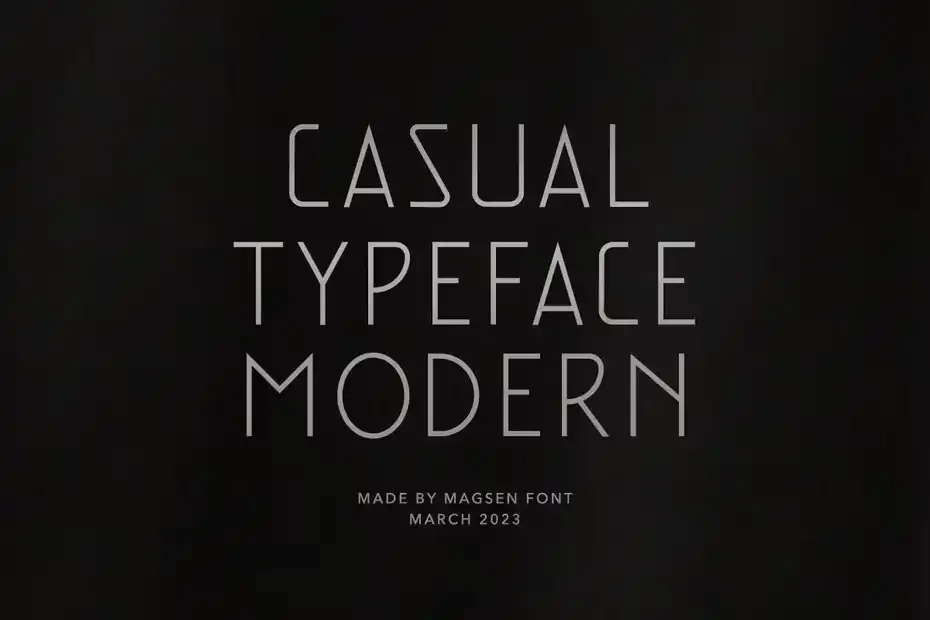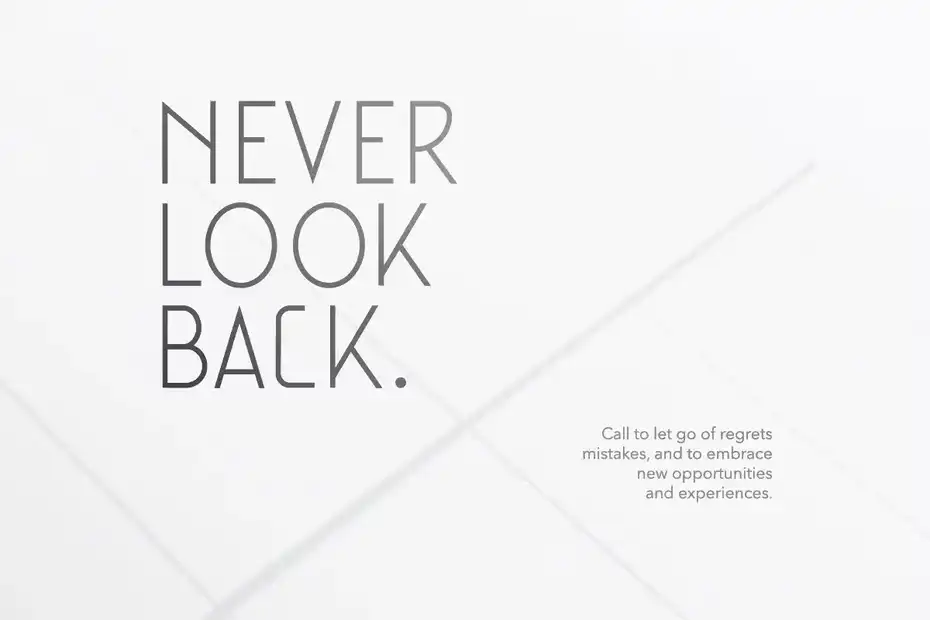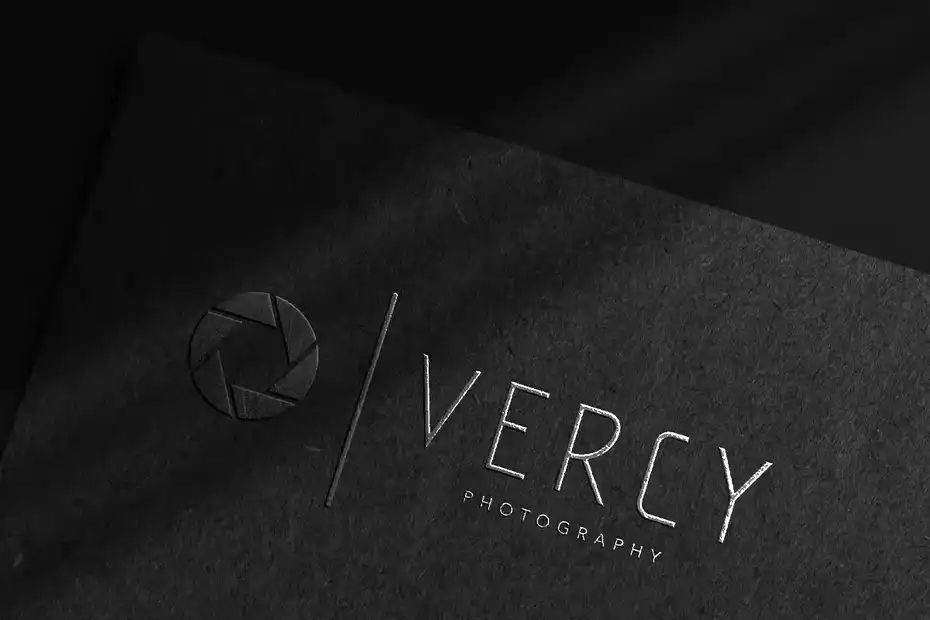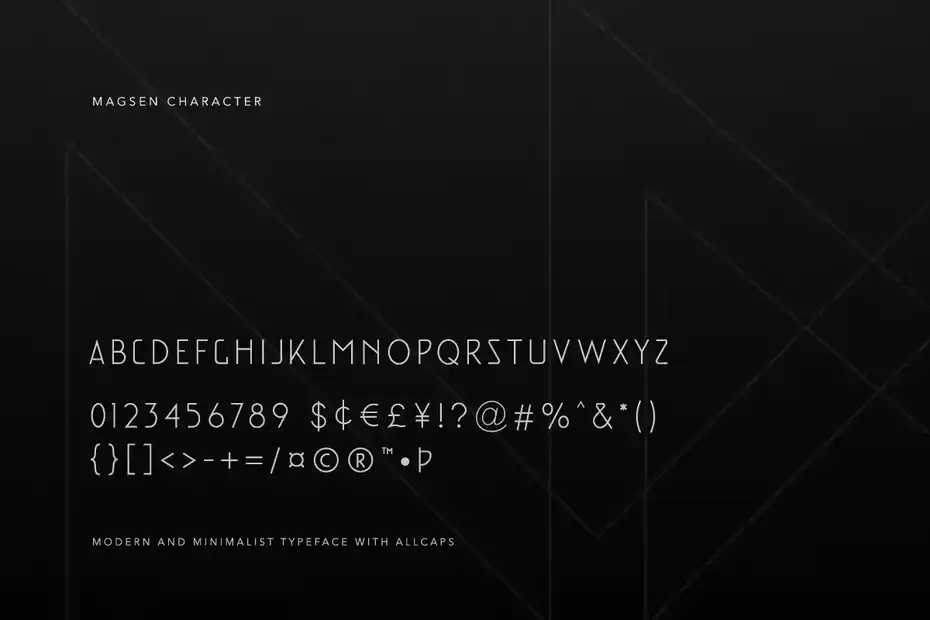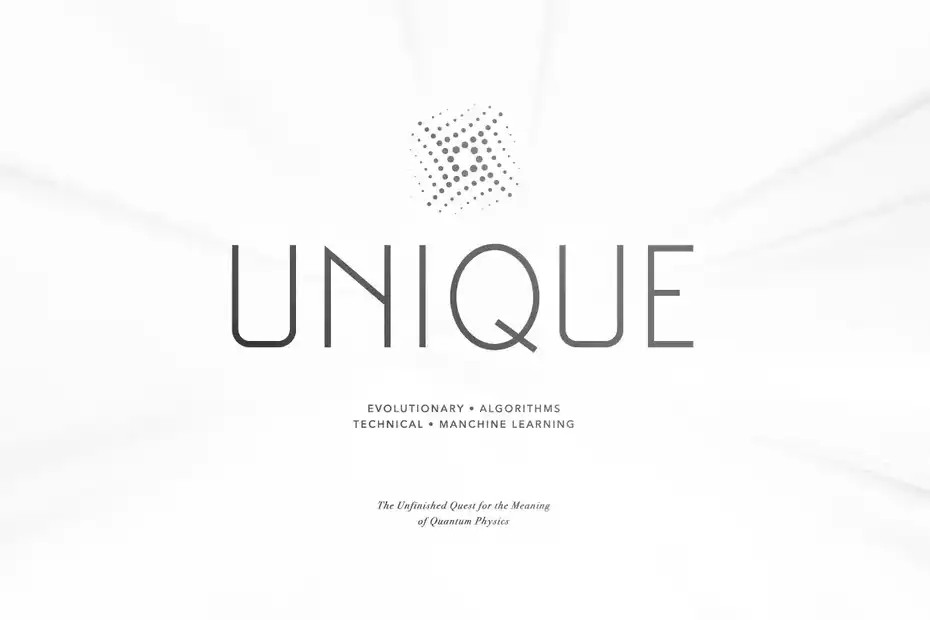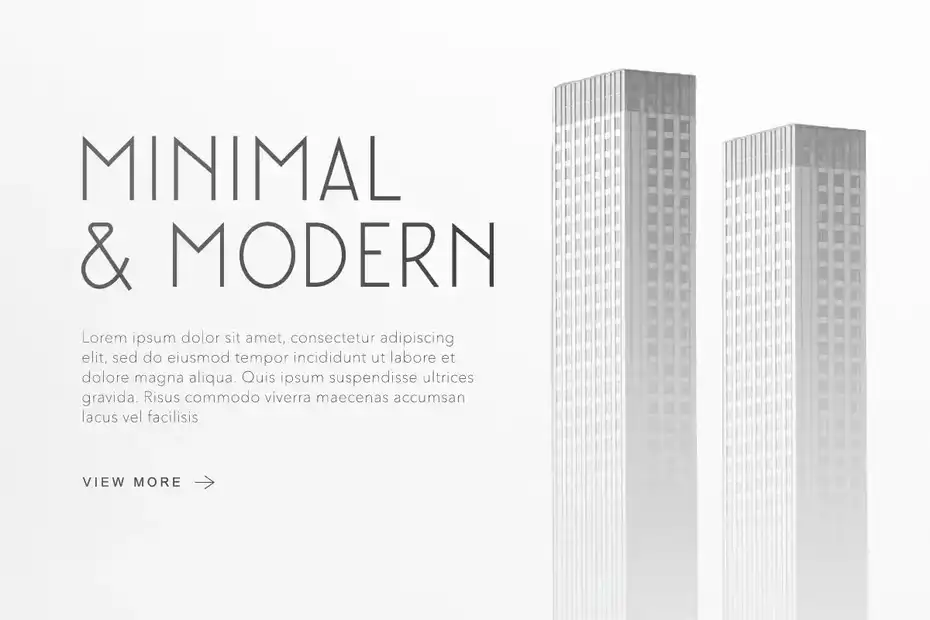
دانلود فونت انگلیسی مدرن Magsen – Modern Font
فونت انگلیسی مدرن Magsen – Modern Font : این مجموعه شامل یک فونت انگلیسی مدرن است که برای کارت ویزیت و غیره مناسب میباشد. فونت های مدرن در کارهای گرافیکی بسیار جذاب و کاربردی هستند، می توانید برای مشاهده فونت های حرفه ای بیشتر دسته بندی فونت انگلیسی مدرن را در سایت سیجی کوک بررسی کنید.